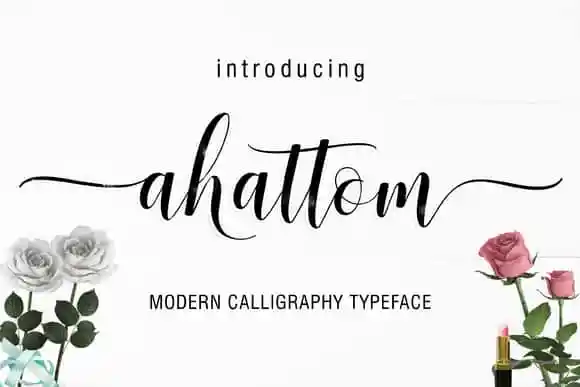
Ahattom Script Font – Download Grátis
Ahattom Script é uma fonte moderna criada com cuidado para cada letra, prometendo textos encantadores e elegantes. Perfeita tanto para projetos como blogs, flyers, cartazes de casamento ou marca, ela abrange uma variedade incrível de usos. Com seu estilo script moderno, Ahattom é ideal para aplicar em tudo o que exige um toque sofisticado e encantador: desde mensagens motivacionais até design gráfico de moda. É perfeita para criar texturas interessantes nos materiais de vestuário ou roupas customizadas. Seja em cartões de convite, embalagens ou papel de parede personalizado, Ahattom traz um toque único à sua identidade visual. Para quem busca uma fonte única e sofisticada, Ahattom é a escolha certa para adicionar profundidade e estilo ao seu design. Com seu design cuidadosamente refinado, esta fonte está repleta de personalização e é um recurso valioso que ajudará a tornar seus projetos ainda mais memoráveis.